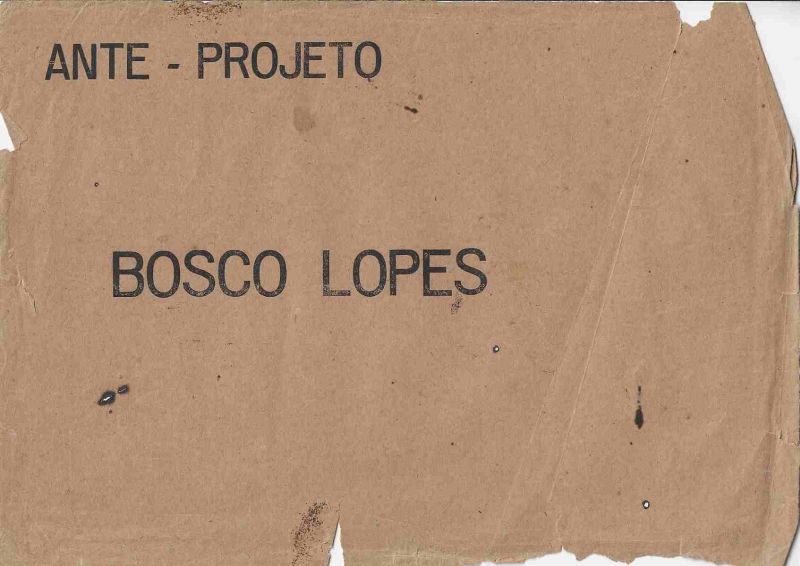
Envelope intitulado Ante Projeto, de Bosco Lopes, concebido como peça gráfica de caráter experimental. A composição apresenta estrutura visual extremamente reduzida, baseada na relação entre tipografia, vazio e suporte.
Envelope intitulado Ante Projeto, de Bosco Lopes, concebido como peça gráfica de caráter experimental. A composição apresenta estrutura visual extremamente reduzida, baseada na relação entre tipografia, vazio e suporte. Na parte superior aparece a inscrição ANTE PROJETO e, ao centro, o nome BOSCO LOPES, ambos impressos em letras maiúsculas sobre papel pardo. A economia formal e a ausência de elementos ilustrativos ou narrativos reforçam a importância do próprio envelope como campo de comunicação e como parte da proposição artística. O título Ante Projeto sugere uma ideia de estágio preliminar, proposta em formação ou estrutura anterior à realização definitiva, aproximando a peça de procedimentos conceituais e experimentais em que o projeto, a linguagem e o suporte assumem valor artístico. O documento pode ser relacionado ao contexto ampliado das práticas de poesia visual, arte conceitual, arte postal, publicações independentes e experimentação gráfica desenvolvidas no Brasil a partir das décadas de 1960 e 1970. A presença exclusiva do nome do artista e do título transforma a superfície do envelope em elemento essencial da obra e enfatiza a materialidade do impresso, a circulação e a comunicação como componentes do trabalho. O objeto possui valor documental para pesquisas sobre Bosco Lopes, redes de arte experimental brasileira, poesia visual, Poema Processo, mail art, arte postal, arte conceitual e produção gráfica independente.TEXTO PARA O PROGRAMA SALSA ENGLISH: Envelope entitled Ante Projeto by Bosco Lopes, conceived as an experimental graphic piece. The composition presents an extremely reduced visual structure based on the relationship between typography, empty space and support. The inscription ANTE PROJETO appears at the top, while the name BOSCO LOPES occupies the central area, both printed in uppercase letters on brown paper. The formal economy and absence of illustrative or narrative elements reinforce the importance of the envelope itself as a field of communication and as part of the artistic proposition. The title Ante Projeto suggests the idea of a preliminary stage, a proposition in formation or a structure preceding final realization, connecting the piece to conceptual and experimental practices in which project, language and support acquire artistic value. The document may be situated within the broader context of visual poetry, conceptual art, mail art, independent publishing and graphic experimentation developed in Brazil from the 1960s and 1970s onward. The exclusive presence of the artist's name and the title transforms the surface of the envelope into an essential component of the work and emphasizes printed materiality, circulation and communication as elements of artistic practice. The object has documentary value for research on Bosco Lopes, Brazilian experimental art networks, visual poetry, Poema Processo, mail art, conceptual art and independent graphic production.
Envelope original de Bosco Lopes com a inscrição Ante Projeto e o nome do artista impressos em letras maiúsculas sobre suporte de papel pardo. A composição utiliza poucos elementos gráficos e explora a relação entre palavra, espaço vazio, materialidade e suporte. O documento é relevante para o estudo da produção experimental brasileira e pode ser relacionado aos circuitos de poesia visual, arte conceitual, arte postal, mail art e publicações independentes. A ausência de data e de outras informações visíveis recomenda cautela na definição cronológica e na atribuição de relações específicas além daquelas documentadas pela própria peça.OBSERVATION TEXT ENGLISH: Original envelope by Bosco Lopes bearing the inscription Ante Projeto and the artist's name in uppercase letters on brown paper. The composition employs a minimal number of graphic elements and explores the relationship between word, empty space, materiality and support. The document is relevant to the study of Brazilian experimental production and may be connected to circuits of visual poetry, conceptual art, mail art and independent publishing. The absence of a visible date or additional documentary information requires caution when establishing chronology or assigning specific historical connections beyond those directly supported by the object.
Envelope entitled Ante Projeto by Bosco Lopes, conceived as an experimental graphic piece. The composition presents an extremely reduced visual structure based on the relationship between typography, empty space and support.